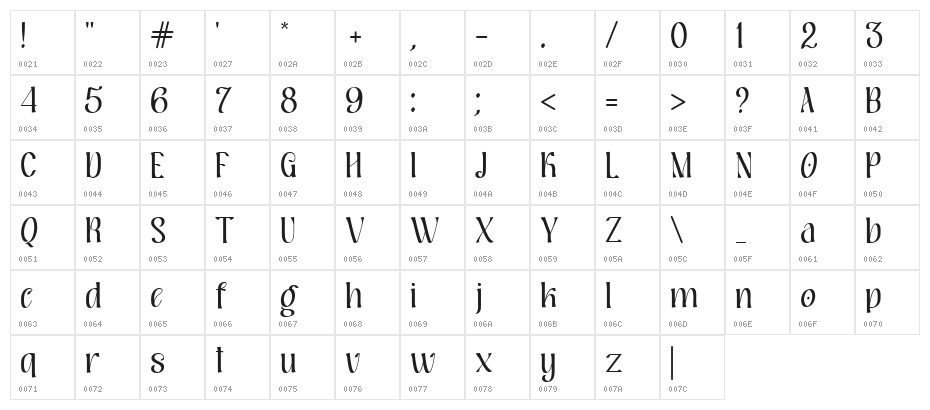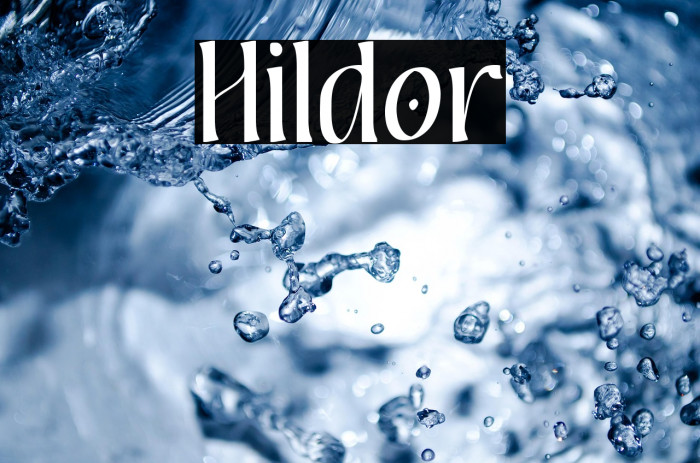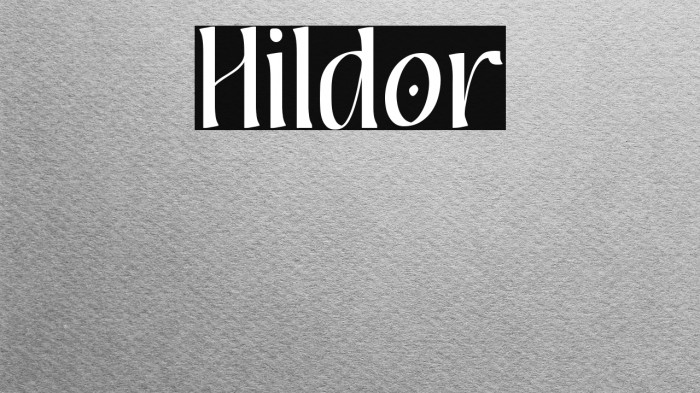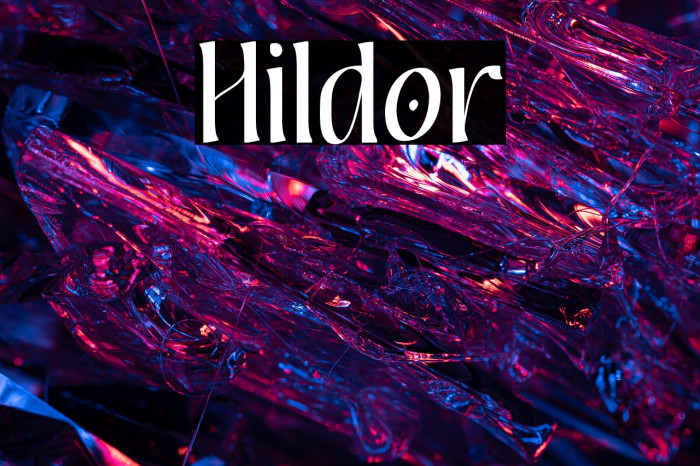
Hildor Font
| Stil general | Modern, Whimsical |
| Caz de utilizare | Headlines, Logos, Invitations |
| Proiecte propuse | Ideal for branding, invitations, posters, and creative design projects that require a touch of elegance and whimsy. |